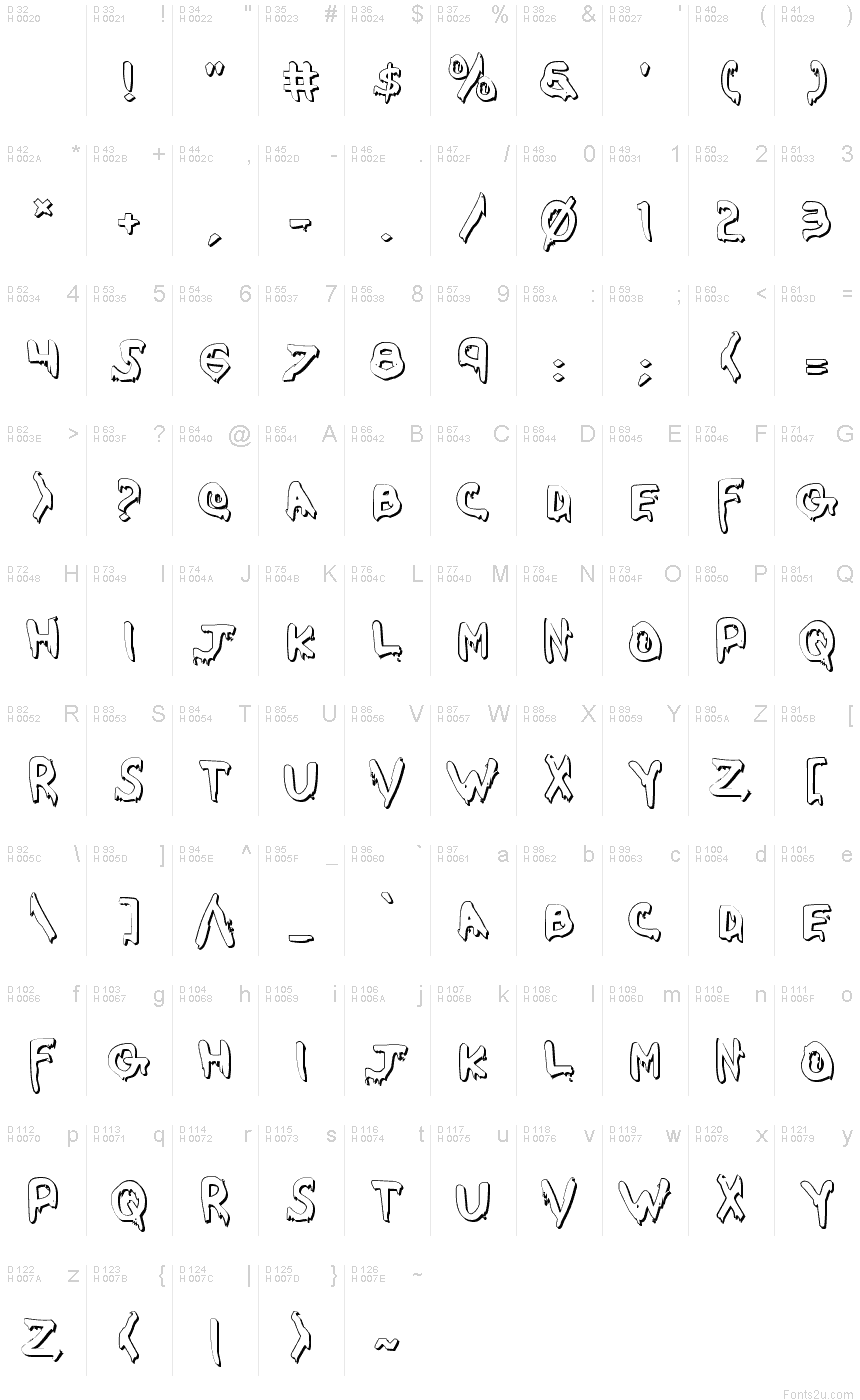
Were-Beast Shadow è un font horror display gratuito di Iconian Fonts, caratterizzato da contorni ribelli e tagli lacerati, simili a graffi. Le sue maiuscole irregolari oscillano tra la minaccia dei cartoni animati e il lettering dei film di mostri, mentre le ombre sfalsate creano una sensazione di profondità ruvida e instabile.
I bordi frastagliati e le ombre striscianti portano un'energia nervosa ai poster horror e alla segnaletica delle attrazioni infestate. Usa questo font gratuito per packaging di Halloween, copertine di film horror, grafica di giochi e promozioni di eventi quando il design richiede uno spavento giocoso piuttosto che un raffinato dramma gotico.